요즘 집에서 나만의 취미를 즐기는 분들이 많아졌죠? 그중에서도 캘리그라피는 적은 공간과 짧은 시간만으로도 큰 즐거움을 줄 수 있는 취미 중 하나예요. 글씨를 예쁘게 쓰는 것에서 나아가, 자신만의 감성과 스타일을 담을 수 있답니다.
이 글에서는 하루 10분 투자로도 충분히 효과를 볼 수 있는 캘리그라피 연습법을 소개할게요. 완전 초보자도 따라 할 수 있도록 기초부터 차근차근 알려드릴 테니 부담 없이 시작해보세요!
🖋 캘리그라피의 매력과 기초
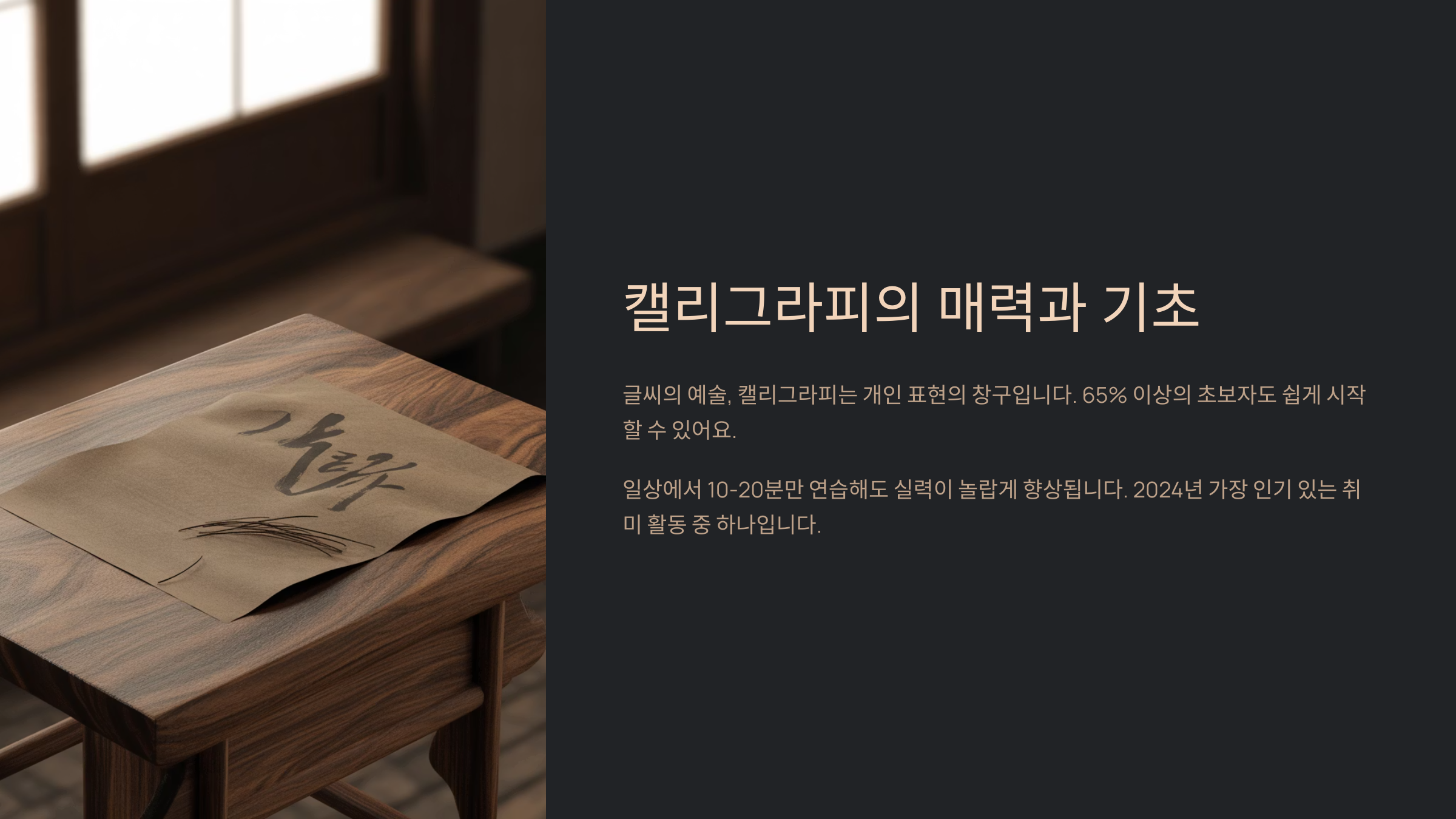
캘리그라피의 매력과 기초
캘리그라피는 단순히 '예쁜 글씨'를 쓰는 것이 아니에요. 손글씨에 감정을 담고, 나만의 개성을 표현할 수 있는 아트 활동이죠. 특히 요즘처럼 디지털 시대에, 손으로 직접 쓰는 글씨는 더욱 특별하게 느껴져요. 감성적인 메시지를 전달하거나, 선물 포장에 정성을 더하고 싶을 때도 캘리그라피가 큰 역할을 해준답니다.처음 시작하는 분이라면 "글씨를 잘 못 쓰는데 할 수 있을까?" 하는 걱정이 들 수 있어요. 하지만 걱정 마세요. 캘리그라피는 타고나는 재능보다 '꾸준함'이 더 중요하답니다. 획을 천천히, 정성 들여 그리는 것부터 시작하면 누구든지 멋진 작품을 완성할 수 있어요.
글씨체도 한 가지만 있는 게 아니에요. 세리프체, 산세리프체, 브러시 스타일 등 다양한 느낌의 글씨체를 연습해보면서 자신만의 스타일을 찾아갈 수 있답니다. 특히 브러시펜을 활용한 연출은 강약 조절로 생동감을 줄 수 있어서 많은 사랑을 받고 있어요.
내가 생각했을 때, 캘리그라피는 그날의 감정과 기분을 그대로 담을 수 있는 일기 같아요. 글씨를 쓰는 시간이 곧 나와 마주하는 힐링의 시간이 된다는 점에서 매력적인 취미예요. 어렵게 생각하지 말고, '그냥 한 번 써볼까?' 하는 마음으로 시작해보세요!
🖋 캘리그라피 스타일 종류 비교표
스타일 특징 사용 펜 난이도 추천 용도 브러시 스타일 굵기 조절이 자유롭고 역동적 브러시펜 중 카드, 선물 포장 고딕체 직선적인 획, 정갈한 인상 캘리그래피 펜 상 로고, 타이포그래피 세리프체 장식적인 느낌, 감성적 딥펜, 브러시 중 명언, 캘리액자 산세리프체 단순하고 현대적인 인상 펠트펜, 붓펜 하 초보자 연습용 다양한 스타일을 연습해보면서 자신이 가장 편하게 느끼는 스타일을 찾는 것도 캘리그라피의 재미예요. 스타일에 따라 느껴지는 감정과 분위기가 다르기 때문에, 원하는 느낌에 맞게 글씨를 바꾸는 것도 가능하답니다. 😊
🖍 준비물과 환경 만들기
캘리그라피 준비물과 환경 만들기 캘리그라피를 시작하기 전에, 기본적인 도구들을 준비해야 해요. 물론 고급 도구가 아니어도 충분히 연습할 수 있답니다. 초보자에게는 너무 비싼 펜보다는 적당한 브러시펜이나 붓펜이 좋아요. 펜촉이 부드럽고 유연한 제품을 선택하면 손에 부담이 덜하고, 다양한 획을 연습하는 데 도움이 돼요.
종이도 중요해요. 일반 프린터용 종이는 잉크 번짐이 생기기 쉬워서 연습용으로는 조금 불편할 수 있어요. 표면이 매끄러운 고급 복사용지나 캘리그라피 전용 연습지를 추천해요. 두께가 적당하고 잉크 흡수가 좋은 종이를 사용하면 스트레스 없이 연습할 수 있어요.
책상 위에 여유 공간을 만들고, 손목을 자연스럽게 움직일 수 있는 자세를 유지하는 것도 중요해요. 손목이나 팔꿈치를 고정하지 않고 부드럽게 움직이도록 해보세요. 너무 긴 시간 연습하는 것보다는, 매일 짧고 집중된 시간에 꾸준히 하는 것이 더 효과적이에요.
조명이 어두우면 눈도 피로하고 글씨 모양도 흐려질 수 있어요. 자연광이 가장 좋지만, 그게 어렵다면 색 온도가 너무 낮지 않은 스탠드를 사용하는 것이 좋아요. 또한 음악을 틀어놓거나 향초를 켜두는 것도 분위기를 살리는 데 도움이 된답니다 🎵
🛠 캘리그라피 도구 비교표
도구 특징 추천 대상 가격대 구입처 브러시펜 굵기 조절 가능, 손쉽게 사용 초보자 저가 문구점, 온라인 딥펜 잉크를 따로 찍어 써야 함 중급자 중~고가 온라인 전문몰 붓펜 붓처럼 부드러운 촉감 모든 수준 중가 대형 문구점 연습 노트 가이드라인 인쇄로 연습 용이 입문자 저가 인터넷 서점 이렇게 간단한 준비만으로도 훌륭한 캘리그라피 환경을 만들 수 있어요. 무조건 비싼 도구를 쓸 필요 없이, 나에게 잘 맞는 도구를 찾는 게 가장 중요하답니다. ✍
✏ 손풀기 스트로크 연습
손풀기 스트로크 연습
캘리그라피는 펜을 쥐는 순간부터 시작되는 예술이에요. 그래서 본격적인 글씨 연습에 들어가기 전, 손을 충분히 풀어주는 스트로크 연습이 필요해요. 단순해 보여도 이 과정이 나중에 글자의 완성도를 높여준답니다.기본 스트로크에는 ‘수직선’, ‘곡선’, ‘점’, ‘사선’, ‘곡선 연결선’ 등이 있어요. 이 스트로크들은 모든 글자의 기반이 되기 때문에 반복 연습이 중요해요. 특히 ‘아래로 힘주기’와 ‘위로 가볍게 올리기’의 강약 조절이 핵심이죠.
예를 들어 ‘a’를 쓸 때는 작은 원을 그리는 듯한 곡선 연습이 필요하고, ‘l’을 쓸 때는 부드러운 수직선이 기본이에요. 단순히 따라 쓰는 것이 아니라, 선 하나하나에 집중하면서 쓰는 것이 중요해요. 이 연습만 잘해도 캘리그라피 실력이 쑥쑥 올라간답니다!
처음에는 손이 떨리거나 선이 삐뚤어질 수 있어요. 하지만 매일 조금씩 스트로크 연습을 하다 보면, 손에 자연스럽게 감각이 생기고 점점 더 예쁜 글씨를 쓸 수 있게 돼요. 이 연습은 명상처럼 마음을 차분하게 해주기도 해요 😌
🌀 기본 스트로크 연습표
스트로크 동작 설명 팁 활용 글자 반복 횟수 수직선 위에서 아래로 일정한 힘으로 손목 고정, 팔꿈치 활용 l, t, k 30회 곡선 C 모양으로 부드럽게 손가락 힘 빼기 c, e, o 30회 사선 45도 기울기로 직선 긋기 종이도 비스듬히 놓기 v, x, y 20회 하트형 곡선 두 개의 반곡선 연결 중앙 포인트 맞추기 m, n 20회 이처럼 매일 손풀기 스트로크를 반복하다 보면 손에 힘이 빠지고, 점점 더 자연스러운 필체가 생겨요. 필체는 하루아침에 생기지 않지만, 하루 10분의 힘이 모이면 놀라운 변화를 가져온답니다 💪
📘 글자 구조와 연습 방법
글자 구조와 연습 방법
스트로크 연습에 익숙해졌다면 이제 본격적으로 글자 연습을 시작할 차례예요. 캘리그라피에서 글자는 단순히 예쁘게 쓰는 것 이상이에요. 각 글자의 구조를 이해하고, 조화롭게 배치하는 감각이 중요하죠. 기본적인 소문자부터 천천히 연습해보는 게 좋아요.소문자는 크게 세 가지 구조로 나눌 수 있어요. x-높이만 사용하는 글자(a, c, e), 아래로 뻗는 글자(g, j, y), 위로 올라가는 글자(b, d, h)예요. 이 구조를 알고 나면 글자의 균형을 잡기가 훨씬 쉬워져요. 또한 글자 간격, 획의 굵기, 경사도 같은 요소들도 함께 고려해야 해요.
처음에는 알파벳 한 글자씩 천천히 연습하고, 점차 단어 단위로 넘어가 보세요. 예를 들어 "hello", "peace", "love" 같은 짧고 감성적인 단어는 연습하기도 좋고 작품으로도 만들기 쉬워요. 반복해서 쓰다 보면 손에 자연스럽게 익고, 실력이 눈에 띄게 향상돼요.
또한 연습할 때는 글자마다 개성을 넣어보는 것도 좋아요. 예를 들어 ‘l’을 길게 뽑거나 ‘o’를 하트 모양처럼 꾸미는 것도 감각을 기르는 방법이에요. 하지만 기본 형태를 해치지 않는 선에서의 꾸밈이어야 해요. 감성과 정확함의 균형이 바로 캘리그라피의 핵심이랍니다 ✨
📏 글자 구성 요소 정리표
요소 설명 예시 문자 중요도 연습 팁 x-높이 기본 글자 높이 a, e, n ★★★★★ 균형 있게 유지 어센더 윗부분 뻗는 부분 b, h, k ★★★☆☆ 길이를 일정하게 디센더 아래로 내려가는 부분 g, j, y ★★★☆☆ 선 끝을 깔끔하게 베이스라인 글자가 놓이는 기준선 모든 글자 ★★★★☆ 수평 유지 꾸준히 글자의 구조를 연습하다 보면 단어 단위의 글씨도 훨씬 정돈된 느낌을 줄 수 있어요. 특히 자주 사용하는 단어들을 연습해두면 다양한 곳에서 유용하게 써먹을 수 있답니다 🎨
🎨 다양한 스타일 시도하기
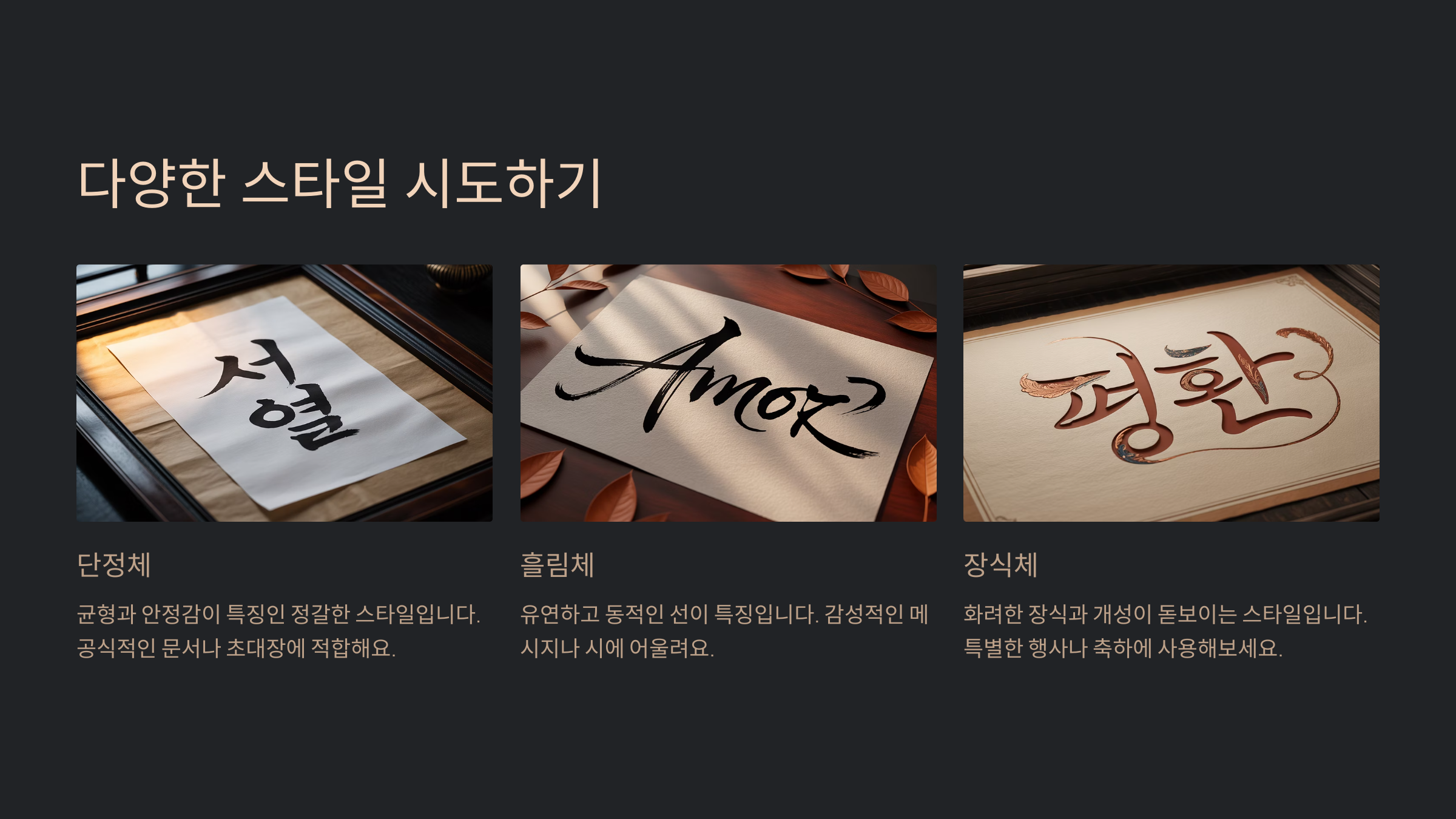
다양한 스타일 시도하기
글자의 구조를 익혔다면, 이제는 다양한 캘리그라피 스타일을 시도해볼 시간이예요! 스타일을 바꾸는 것만으로도 같은 문장이 전혀 다른 감성으로 표현될 수 있어요. 캘리그라피의 매력은 바로 이 무한한 창의성에 있죠.대표적인 스타일로는 브러시 스타일, 만년필 느낌의 필기체, 고딕체, 자유곡선 스타일 등이 있어요. 각 스타일은 표현하고자 하는 분위기에 따라 선택할 수 있어요. 예를 들어 축하 카드에는 화려한 브러시 스타일이 잘 어울리고, 일기에는 자연스러운 필기체가 잘 맞아요.
스타일을 익히는 가장 좋은 방법은 따라 쓰기예요. SNS나 핀터레스트에서 다양한 캘리그라피 샘플을 참고해서 눈으로 보고 손으로 따라 해보세요. 처음엔 똑같이 안 될 수도 있지만, 여러 스타일을 흉내 내는 과정을 통해 나만의 감각이 자라나요.
또한 색깔을 바꿔보는 것도 추천해요. 단색으로만 쓰던 글씨에 컬러펜을 섞으면 전혀 다른 분위기가 연출돼요. 예를 들어, 첫 글자만 강조해서 금색으로 써보거나, 문장 중 중요한 단어를 붉은색으로 써보는 것도 감각을 키우는 방법이랍니다 🌈
🎨 캘리그라피 스타일별 느낌표
스타일 느낌 추천 상황 난이도 연습 팁 브러시 스타일 감성적이고 부드러움 감성 엽서, 손편지 중 강약 조절 집중 고딕체 중후하고 클래식함 포스터, 로고 상 정렬 연습 필요 자유곡선체 자유롭고 개성 넘침 일러스트, 낙서풍 아트 하 제한 없이 써보기 펜슬 스타일 차분하고 섬세함 메모, 스케치북 하 연필로 밑그림 그리기 다양한 스타일을 연습해보면 글씨 쓰는 것이 점점 더 재미있어져요. 어느 날 갑자기 나만의 스타일이 생기고, 그게 누군가에겐 작품처럼 느껴질 수도 있어요. 그래서 캘리그라피는 진짜 마법 같아요 🪄
⏰ 10분 루틴으로 습관 만들기
10분 루틴으로 습관 만들기 캘리그라피 실력을 키우는 데 가장 중요한 건 '꾸준함'이에요. 하루 10분씩 짧게라도 연습하는 루틴을 만들면, 어느 순간 글씨가 자연스럽고 예뻐져 있는 걸 느낄 수 있답니다. 아침이나 자기 전, 하루 중 마음이 차분해지는 시간을 정해두고 해보는 걸 추천해요.
A2. 초보자에게는 브러시펜이 좋아요. 굵기 조절이 쉬워서 다양한 스트로크를 연습하기에 적합해요.
Q3. 하루에 얼마나 연습해야 효과가 있나요?
A3. 하루 10분이라도 꾸준히 하는 것이 가장 중요해요. 매일 조금씩 연습하면 금방 실력이 늘어요!
Q4. 왼손잡이도 캘리그라피 할 수 있나요?
A4. 물론이에요! 펜을 약간 옆으로 기울이거나, 각도에 맞게 종이 위치를 조정하면 충분히 가능하답니다.
Q5. 디지털 캘리그라피도 가능한가요?
A5. 네! 아이패드나 타블렛을 이용하면 디지털로도 감성적인 글씨를 연습하고 활용할 수 있어요.
Q6. 연습지를 꼭 써야 하나요?
A6. 필수는 아니지만, 가이드라인이 있는 연습지는 초보자가 글씨 균형을 잡는 데 큰 도움이 돼요.
Q7. 색상 조합은 어떻게 정하나요?
A7. 기본은 검정, 회색으로 시작하고 익숙해지면 포인트 컬러(금, 빨강, 파스텔톤)를 하나씩 섞어보면 좋아요.
Q8. 완성한 작품은 어디에 활용하나요?
A8. 엽서, 카드, 포장지, 다이어리, 액자 등 다양하게 활용할 수 있어요. SNS에 공유해서 자랑도 할 수 있죠!